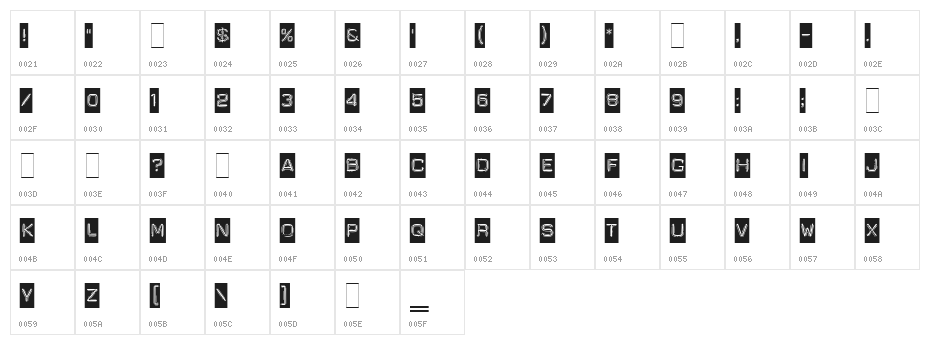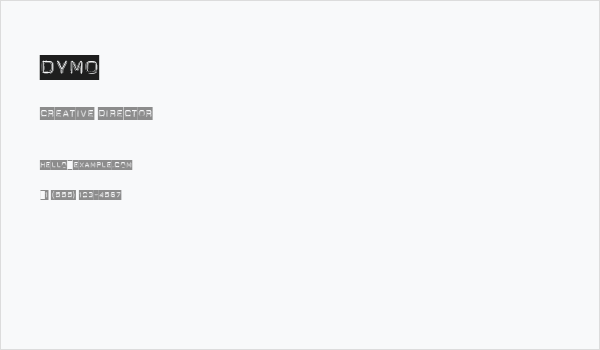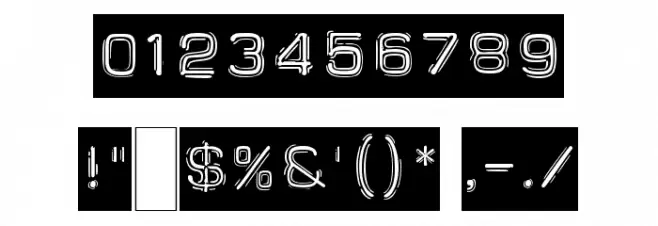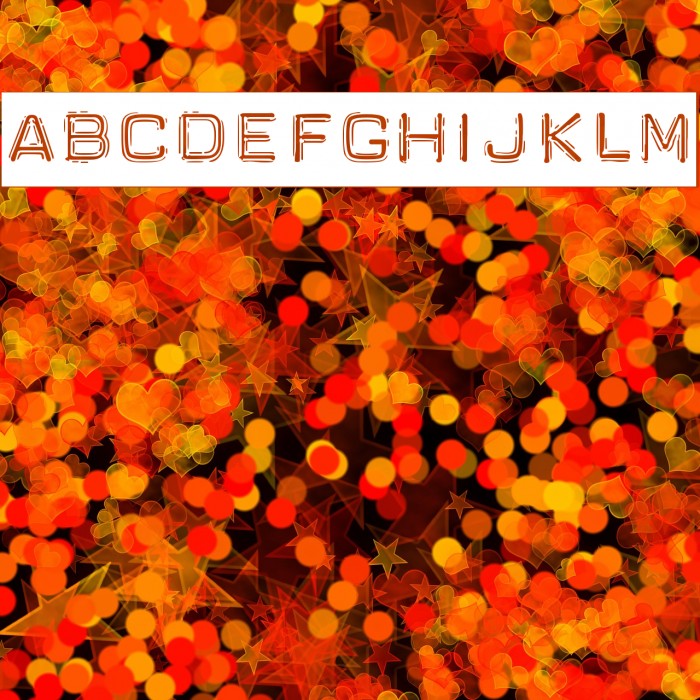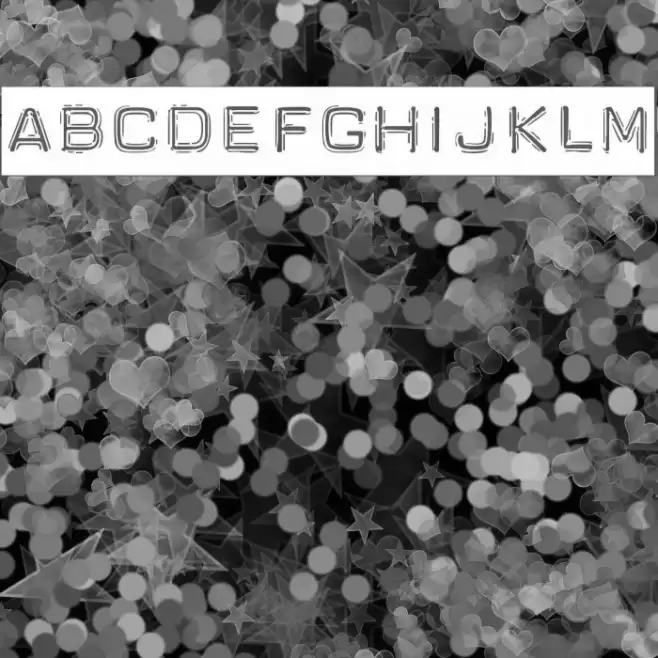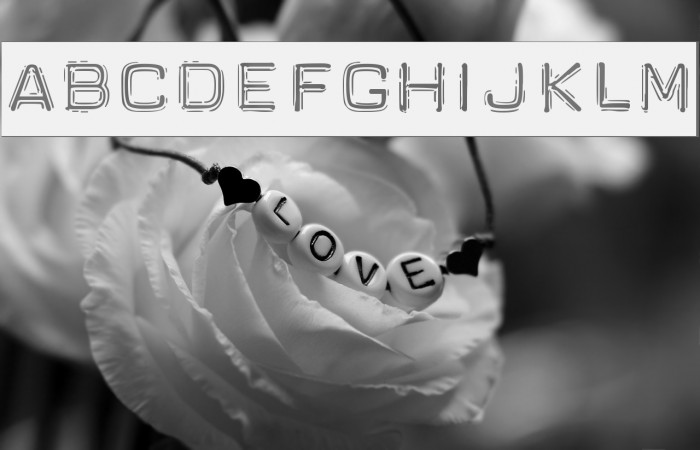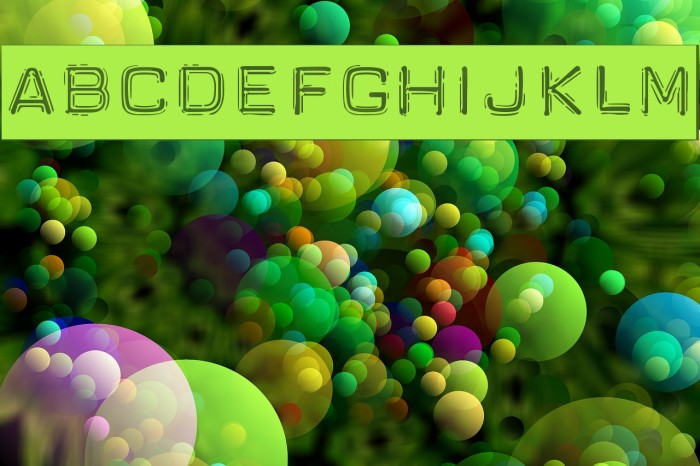
Dymo Font
| Style général | Retro, Industrial |
| Cas d'utilisation | Logos, Signage, Branding |
| Projets proposés | Ideal for projects requiring a retro or industrial aesthetic, such as vintage labels, signage, or branding materials. |